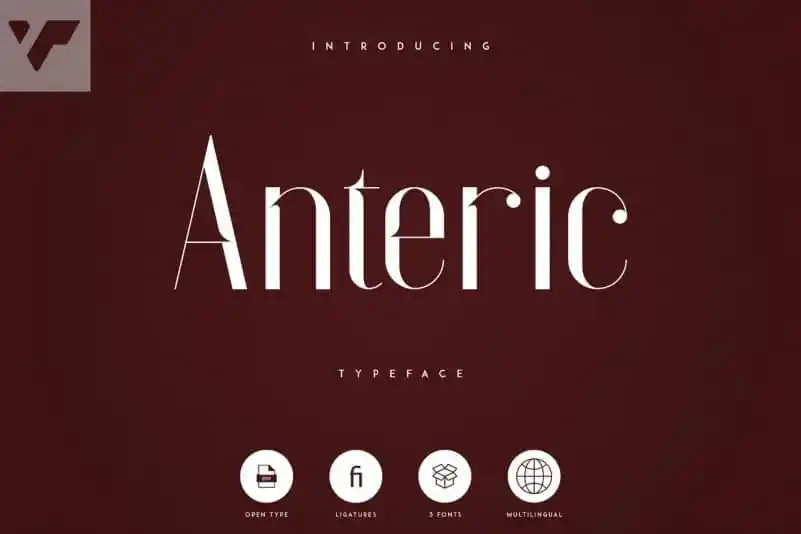
Anteric Display Typeface With 3 Weights – Fonte Grátis
Anteric Display Typeface With 3 Weights
A Anteric Display Typeface é uma fonte vintage e elegante que oferece três pesos diferentes. Seu design meticuloso permite-lhe acomodar ambientes tanto grandes quanto pequenos, tornando-a perfeita para um amplo gama de aplicações gráficas. Ela inclui ligaturas que tornam as palavras mais fluidas e suaves ao serem escritas, enquanto suporta múltiplas línguas, ampliando ainda mais suas possibilidades criativas. A Anteric Display Typeface é uma fonte versátil e moderna, projetada para se adaptar a qualquer tipo de projeto em que ela seja utilizada. Seja você um designer gráfico ou um editor de texto, esta fonte traz estilo e sofisticação sem gastar muito tempo no processo de edição. Com três pesos disponíveis, é fácil encontrar o peso certo para atender às suas necessidades específicas. Esse design sólido em três pesos permite que você personalize sua mensagem de maneira única. A Anteric Display Typeface, com seus detalhes meticulosos e suporte a múltiplas línguas, certamente encaixa-se perfeitamente entre os recursos gráficos modernos.